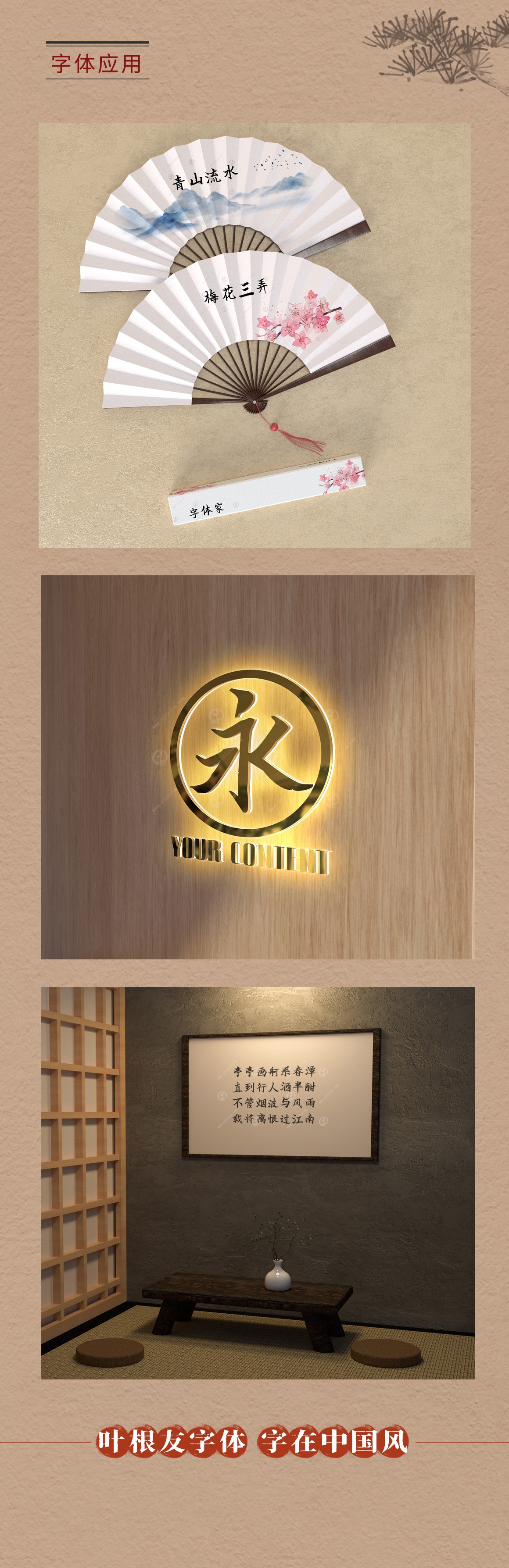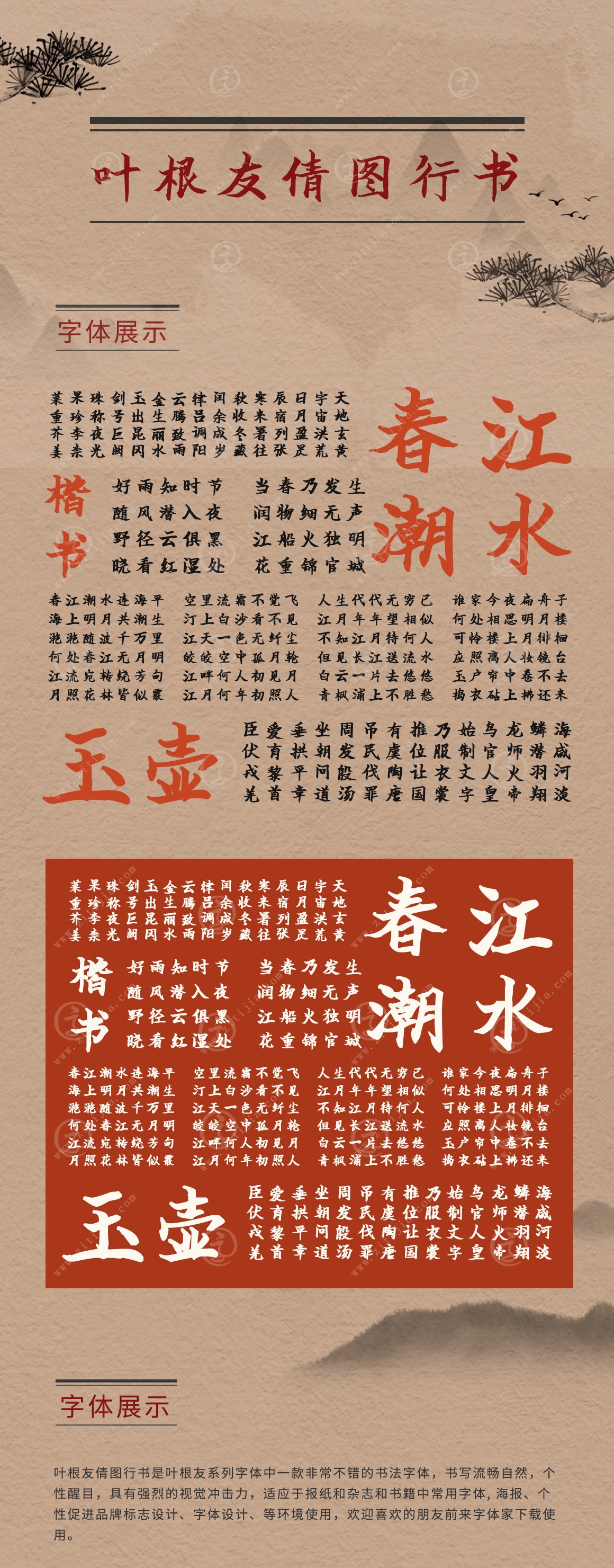
葉根友倩圖行書(shū)是一款非常不錯(cuò)的手寫(xiě)字體,書(shū)寫(xiě)流暢自然,具有強(qiáng)烈的視覺(jué)沖擊力,適應(yīng)于報(bào)紙和雜志和書(shū)籍中常用字體, 海報(bào)、個(gè)性促進(jìn)品牌標(biāo)志設(shè)計(jì)、字體設(shè)計(jì)、等場(chǎng)景使用。